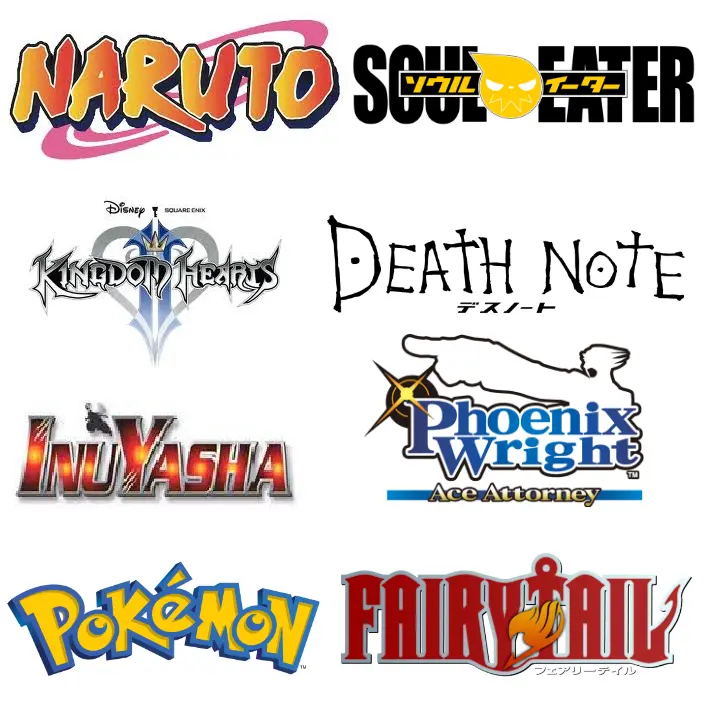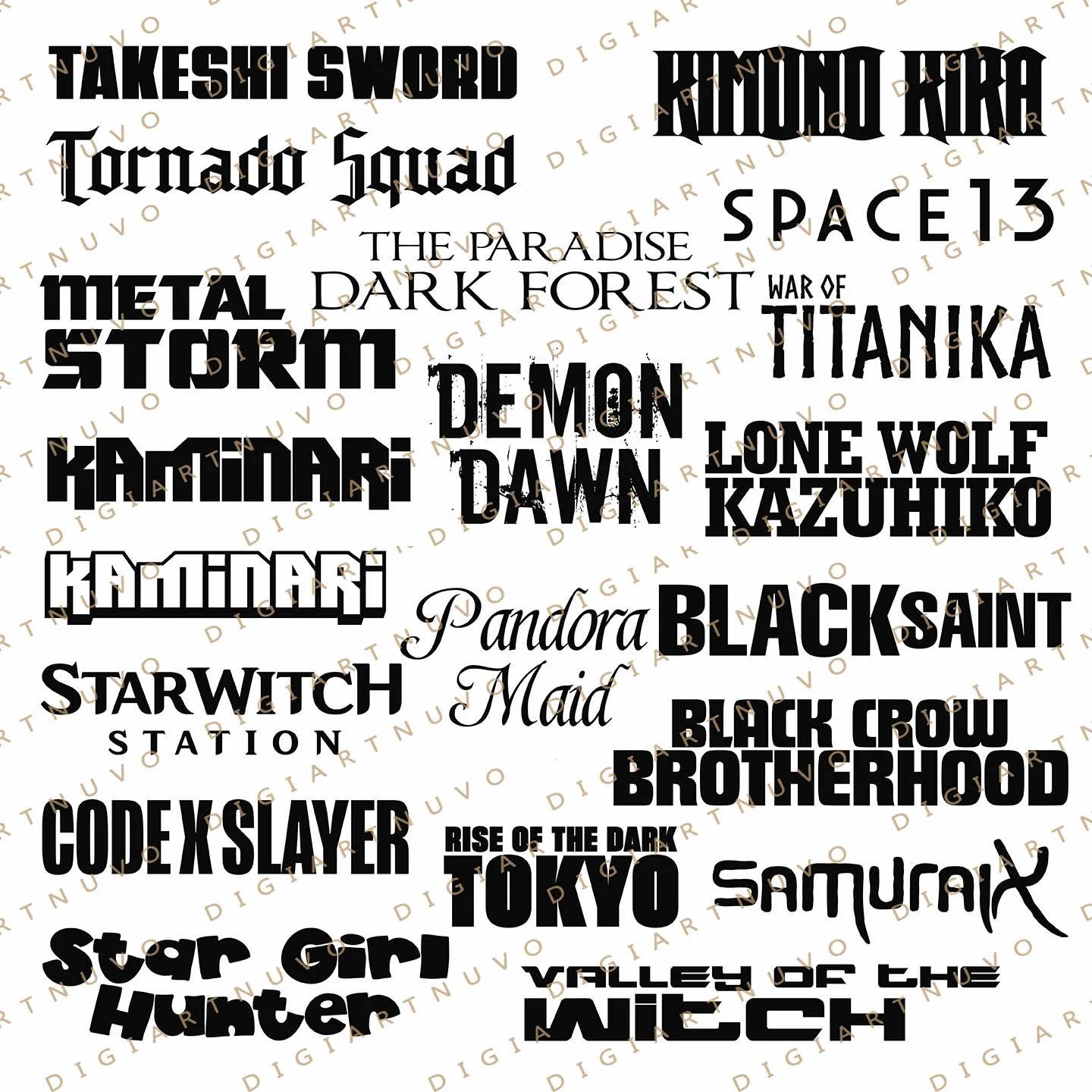
Mejores fuentes para títulos de anime
Elegir la fuente ideal para el título de un anime es crucial. Una tipografía expresiva transmite valores, ideas y la atmósfera general del proyecto. Es la primera impresión, la portada que define el juicio inicial del espectador. Debe causar impacto inmediato, porque en el entorno saturado de información actual, una segunda oportunidad para captar la atención es un lujo que pocas veces se tiene.
¿Qué hace una buena fuente para títulos de anime?
Las fuentes se dividen en fuentes de texto y fuentes de títulos (display). Las fuentes de texto son para párrafos, deben ser legibles y cómodas en cualquier dispositivo. Son sencillas y limpias. La prioridad es la comodidad de lectura, con tamaños que van de 6 a 14-16 puntos.
Las fuentes display se usan en tamaños grandes, titulares y elementos destacados para llamar la atención. Son expresivas y con detalles llamativos. Sus tamaños suelen ser de 14 puntos en adelante.
Dentro de las fuentes display, encontramos las fuentes para títulos, ideales para portadas, páginas de título y encabezados. A menudo tienen un juego de caracteres reducido o solo mayúsculas. Sus tamaños empiezan desde los 16 puntos.
Las fuentes de texto tienen requisitos más sencillos que las fuentes expresivas. Una fuente de texto puede usarse para un titular, dependiendo del diseño. Sin embargo, usar una fuente display para texto corrido no es recomendable.
Cómo elegir la fuente perfecta para tu título de anime
Elegir la fuente para el título de tu anime es subjetivo y depende de tus objetivos. Selecciona la que mejor se adapte a tu proyecto, no solo la que más te guste. No hay reglas estandarizadas, cada proyecto necesita una fuente diferente.
Una buena fuente para títulos de anime debe:
• Acoplarse al estilo de tu proyecto y transmitir las emociones y valores adecuados.
• Diferenciarse de la fuente principal para captar la atención. La intensidad de esta diferencia depende de tus objetivos.
• Verse correctamente en todos los dispositivos . Es fundamental, sobre todo si se trata de una fuente gratuita.
Combinando fuentes: Título y cuerpo de texto
Si ya tienes una fuente principal y buscas una expresiva para combinarla, o si buscas una pareja de fuentes, sigue estas recomendaciones:
• Elige fuentes que coincidan estéticamente con tu proyecto.
• Define el rol de cada fuente: una principal y otra para acentos.
• Sigue el principio del máximo contraste. Las fuentes deben tener una idea similar, pero con visuales contrastantes.
El proceso es similar a elegir un atuendo. Una fuente sans-serif básica es como unos vaqueros. Dependiendo de cómo la combines, puedes hacerla más formal o relajada. Una serif elegante sería como una chaqueta que le da un toque formal.
Usando la misma fuente para texto y títulos
Con recursos limitados, puedes usar una misma fuente en diferentes tamaños y pesos. Necesitas una fuente de texto legible en tamaños pequeños, pero que también se vea bien en tamaños grandes y con negritas.
Mejores Fuentes para Títulos de Anime
Aquí te presentamos una lista de fuentes, incluyendo algunas opciones gratuitas y de pago:
Fuente Descripción Estilo
TT Espina Serif llamativa, alta contraste, serifs expresivos. Ideal para proyectos de arte o diseño decorativo. Romántica, misteriosa
TT Ricks Serif moderna, audaz, con serifs afiladas. Para proyectos donde se busca atreverse. Moderna, audaz
TT Moons Serif moderna, elegante, contraste alto. Ideal para revistas, libros y periódicos. Elegante, sobria
TT Geekette Serif variable, formas fluidas, única y estilosa. Para impresión y web. Original, distintiva
TT Alientz Familia con serif expresiva y sans-serif sencilla. Para proyectos que mezclan lo racional e irracional. Cool, audaz
TT Phobos Serif suave, formas fluidas, contraste medio. Ideal para proyectos de hogar o confitería. Suave, gentil
TT Marxiana Elzevier Inspirada en una revista del siglo XIX, moderna y versátil. Ideal para periódicos, revistas y libros. Clásica, versátil
TT Ricordi Allegria Sans-serif de alto contraste, dinámica. Resalta la elegancia y exquisitez. Elegante, exquisita
TT Ricordi Greto Sans-serif con toques de serif, histórica y contemporánea. Para portadas, posters y web. Distintiva, versátil
TT Ricordi Marmo Serif moderna, neutra e inusual. Para proyectos formales e informales. Moderna, versátil
Futura Clásica y legible. Clásica, moderna
Nexa Rust Geométrica, moderna. Moderna, geométrica
Bree Serif Elegante, con serifs. Elegante, clásica
Proxima Nova Versátil, limpia. Moderna, limpia
Cooper Black Clásica, audaz. Clásica, audaz
Museo Geométrica, moderna. Moderna, geométrica
Bodoni Clásica, elegante. Clásica, elegante
Gilroy Moderna, versátil. Moderna, versátil
Helvetica Clásica, legible. Clásica, legible
ITC Avant Garde Gothic Moderna, geométrica. Moderna, geométrica
Recuerda que la elección de la fuente para tu título de anime es un proceso personal que depende del contexto de tu proyecto. Experimenta, analiza proyectos de otros diseñadores y no te limites a una sola opción.